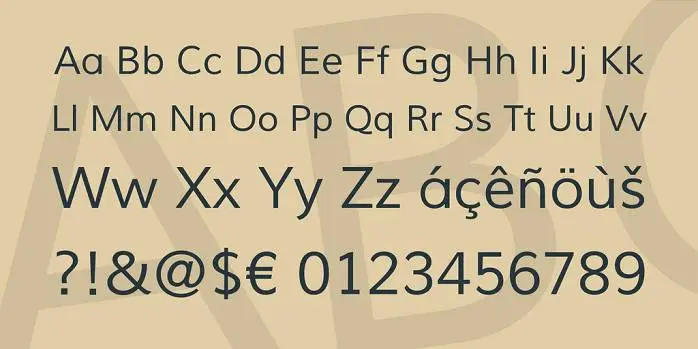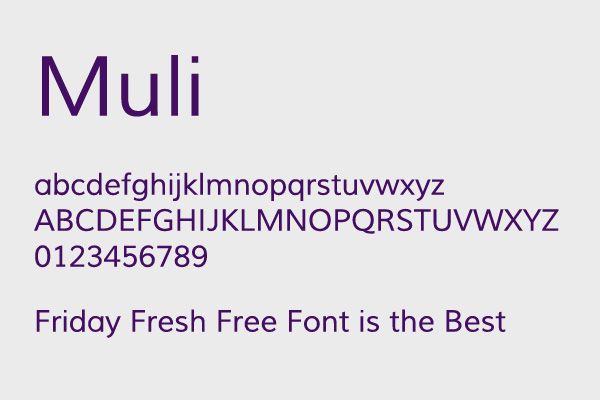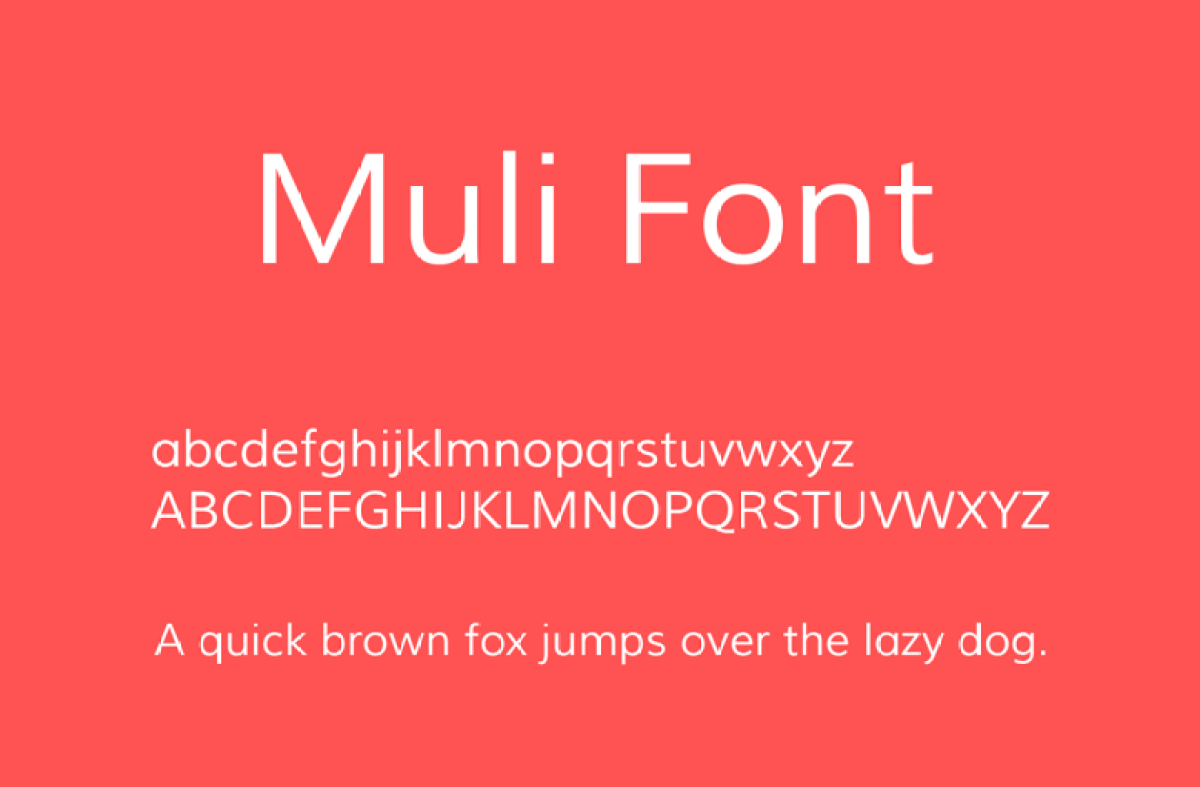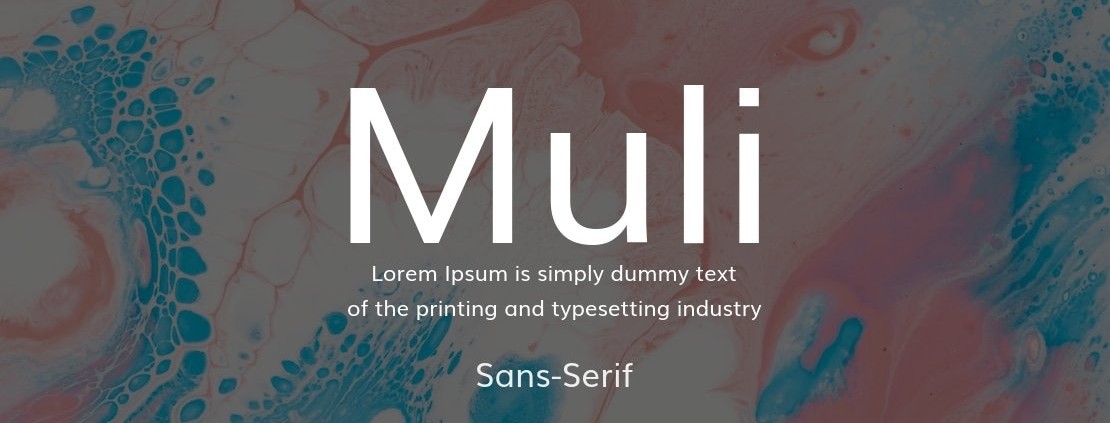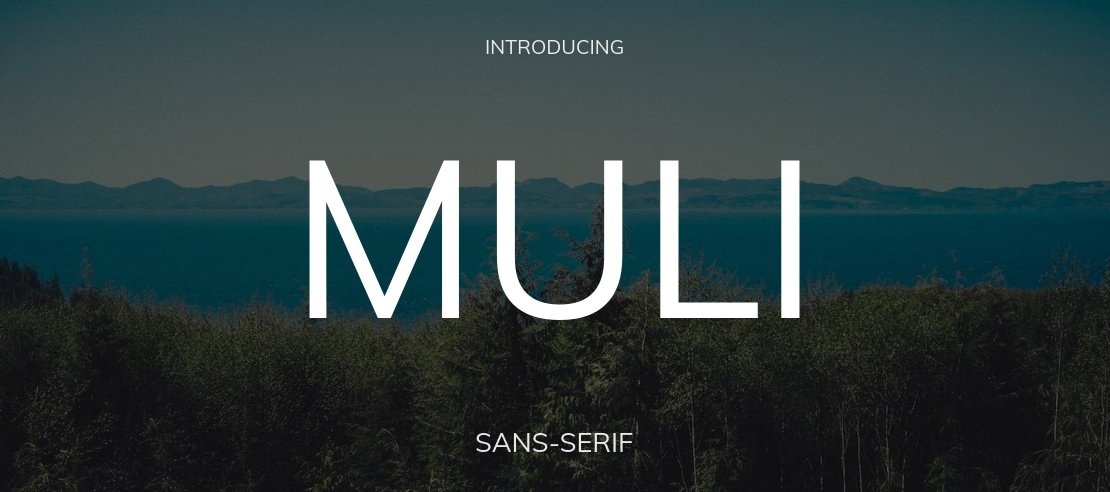
Font Muli Việt hóa (nay được phát triển mở rộng với tên gọi Mulish trên Google Fonts) là bộ phông chữ không chân (Sans-serif) theo phong cách tối giản, thanh lịch và chuẩn mực được sáng tạo bởi nhà thiết kế Vernon Adams. Với cấu trúc chữ mở, độ dày nét đồng đều và tỷ lệ hình học cân bằng hoàn hảo, Muli là lựa chọn số một cho các dự án thiết kế giao diện số, nhận diện thương hiệu công nghệ và bao bì mỹ phẩm theo đuổi phong cách Minimalism. Doozypack.vn cung cấp link download font Muli Việt hóa chuẩn kỹ thuật, giúp bạn sở hữu phông chữ đẳng cấp mà không lo gặp bất kỳ lỗi hiển thị dấu thanh nào khi thiết kế in ấn.
Đặc điểm thẩm mỹ độc đáo của bộ font Muli
Muli không tìm kiếm sự phô trương cầu kỳ; sức hút của nó đến từ sự trong trẻo, trung tính và khả năng truyền tải thông tin một cách minh bạch nhất.
Phong cách Sans-serif tối giản và thanh lịch
Đặc trưng lớn nhất của Font Muli Việt hóa là các đường nét được thiết kế gọn gàng, loại bỏ hoàn toàn mọi chi tiết thừa thãi. Cấu trúc chữ sở hữu độ mở lớn (open counters) cùng những đường cong hình học mềm mại nhẹ nhàng, tạo cảm giác thân thiện, tinh tế và cực kỳ hiện đại. Khi đặt Muli làm tiêu đề hoặc nội dung trên bao bì, sản phẩm của bạn sẽ ngay lập tức toát lên vẻ sạch sẽ, thuần khiết và tạo dựng niềm tin vững chắc với người tiêu dùng.
Độ dễ đọc tuyệt vời trên mọi chất liệu và kích thước
Các ký tự của Muli sở hữu tỷ lệ x-height thoáng đãng cùng khoảng cách chữ (kerning) được tính toán khoa học. Nhờ đó, phông chữ này duy trì được độ rõ nét đáng kinh ngạc từ màn hình kỹ thuật số cho đến các bản in thực tế, giúp người xem dễ dàng tiếp nhận thông tin bảng thành phần, địa chỉ sản xuất hay hướng dẫn sử dụng mà không hề bị mỏi mắt.
Khi ứng dụng các phông chữ tối giản vào thị trường trong nước, sự chỉn chu về dấu câu là yếu tố quyết định đến tính chuyên nghiệp của bản thiết kế:
- Khắc phục triệt để lỗi dấu tiếng Việt: Phiên bản Việt hóa đã được đội ngũ thiết kế trau chuốt thủ công từng dấu câu. Các dấu sắc, huyền, hỏi, ngã, nặng được vẽ thanh thoát, đặt ở vị trí cân đối so với thân chữ, không gây cảm giác chắp vá hay đè nét làm mất tính thẩm mỹ tối giản.
| Biến thể Font | Đặc điểm thị giác | Ứng dụng đề xuất tại Doozypack.vn |
| Muli Light | Thanh mảnh, tinh tế, nhẹ nhàng | Dùng cho các ghi chú nhỏ, thông số kỹ thuật trên bao bì mỹ phẩm. |
| Muli Regular | Cân đối, thông thoáng, dễ đọc | Dùng cho nội dung hướng dẫn sử dụng, bảng thành phần (Body text). |
| Muli Bold / ExtraBold | Dày dặn, vững chãi, nổi bật | Dùng làm tiêu đề chính, tên sản phẩm hoặc logo thương hiệu. |